Les bests of de la fonderie Latinotype.
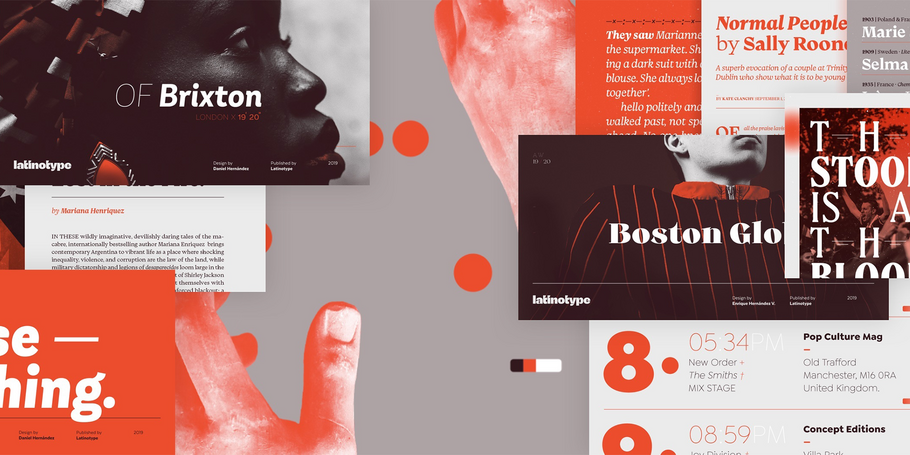
Sélectionnés par le Monotype Studio.
Latinotype.
Première fonderie numérique du Chili, Latinotype a pour objectif de "concevoir de nouvelles polices de caractères en remixant les diverses influences liées à notre identité sud-américaine avec des produits de haute qualité pour l'industrie du design contemporain". Et c'est ce que les deux fondateurs font depuis la création de leur fonderie en 2007. Luciano Vergara et Daniel Hernández ont créé une collection de polices de caractères en pleine expansion dans un large éventail de genres. Spécialisé dans l'affichage coloré et les polices de caractères, le nom du groupe "Latinotype" souligne le lien fort qu'ils ressentent avec leur identité culturelle.
Mixta
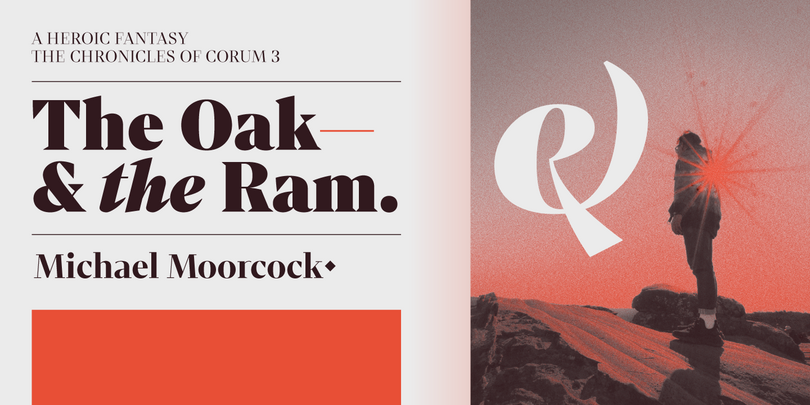
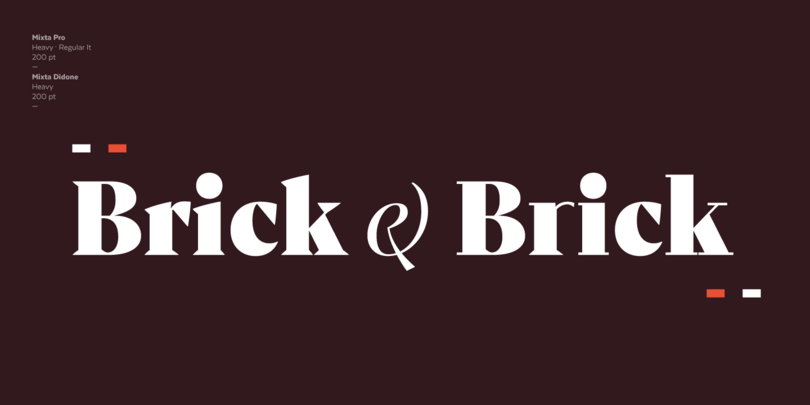
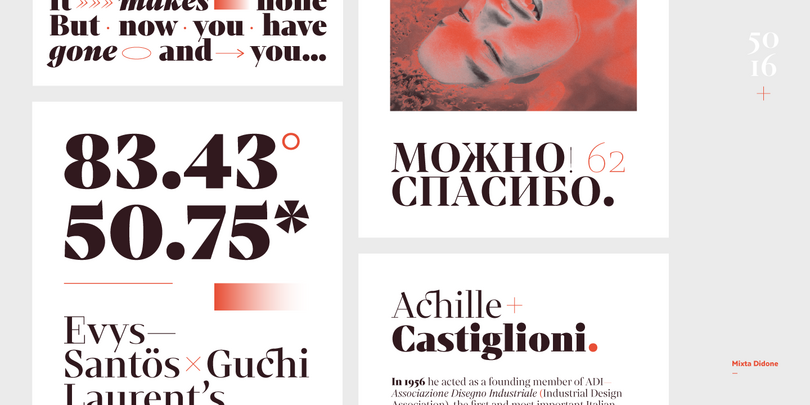
Mixta est une police de caractères sans empattement contemporain, inspirée par l’idée de mélanger différents types de terminaux afin de donner à la police une apparence singulière – des didones historiques aux sans contemporains. Mixta est proposée avec un jeu de 1200 caractères qui prend en charge plus de 200 langues latiesn. Cette police a été spécialement conçue pour la stratégie de marque, la publicité, la conception éditoriale et l’utilisation à la télévision et dans les réseaux sociaux.
Recoleta
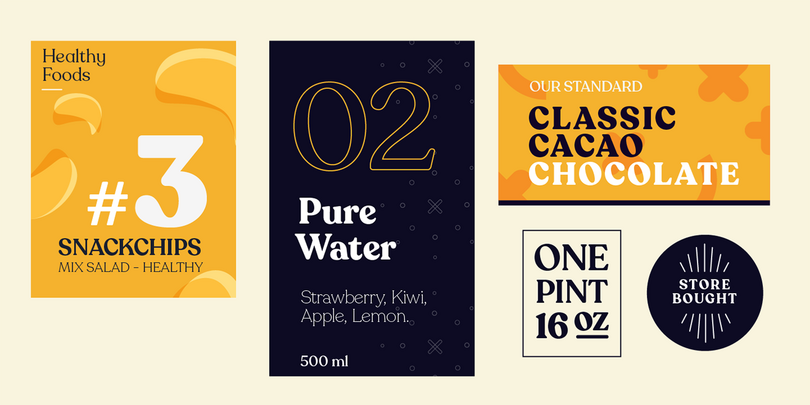
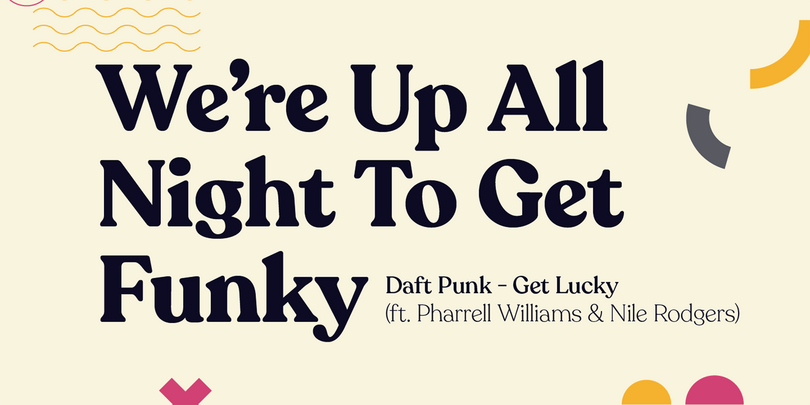
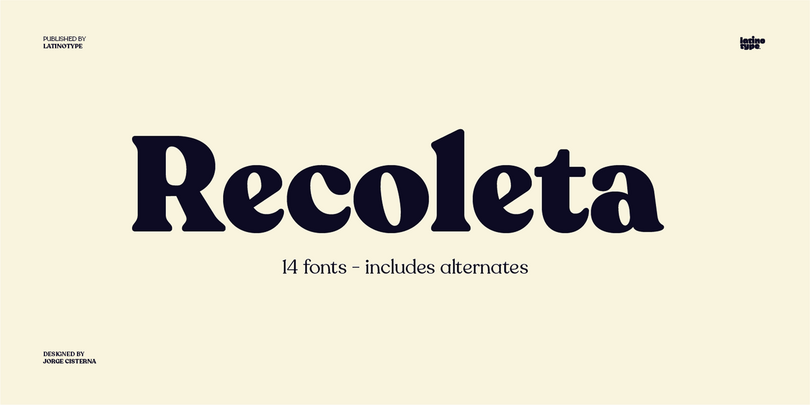
Tout comme la cuisine de grand-mère, Recoleta combine une variété d’ingrédients – de diverses polices de caractères populaires des années 1970 – comme les formes douces et délicates que l’on trouve dans Cooper ou les traits fluides et anguleux dans Windsor – mélangés en un seul design qui présente des saveurs familières, mais fraîches et modernes.
Corporative Slab
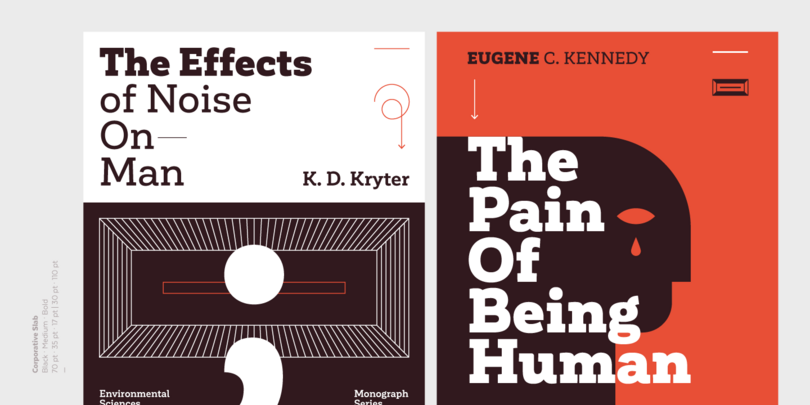
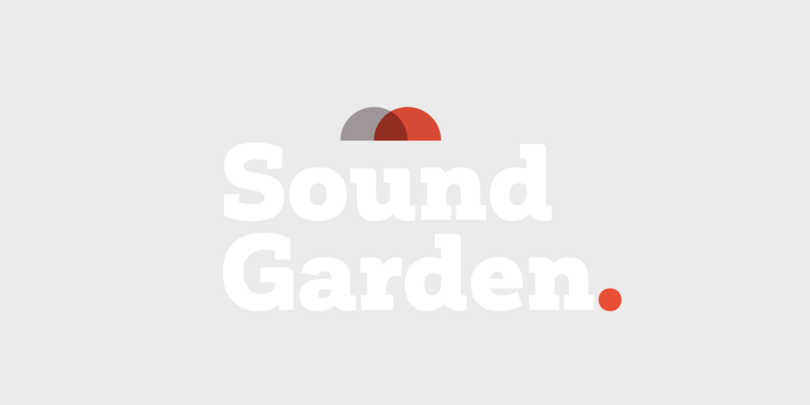
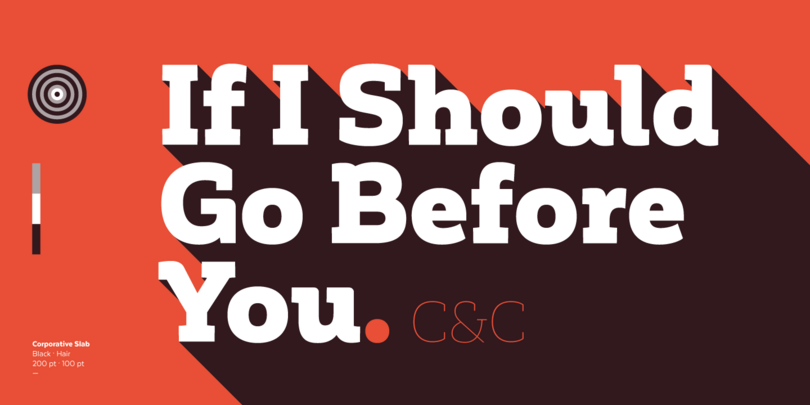
Les serifs épais du Corporative Slab lui donnent une forte personnalité. Son architecture fondamentale et ses bords arrondis lui confèrent un équilibre parfait avec le Corporative original. Le Corporative Slab est idéal pour une utilisation à grande échelle et convient également aux petites tailles.
Branding
Branding, une police de caractères moderne pour des besoins modernes ! Elle a été spécialement conçue pour répondre aux besoins esthétiques et fonctionnels contemporains ; l’interprétation d’un caractère moderne du point de vue du concepteur. Cette police convient bien aux logos, aux isotypes, aux textes courts, etc. Elle se décline en 7 graisses, allant du Thin au Black, avec les italiques correspondantes, et comprend un jeu de 544 caractères qui supporte 128 langues différentes. Les accents européens, les chiffres à l’ancienne et les multiples variantes sont également inclus.
Galeana
Galeana est une réinterprétation des polices de caractères à saveur latino-américaine utilisées pour les conceptions éditoriales européennes telles que les magazines Plastique et Zembla. Cette superfamille est composée de 4 sous-familles : Compressed, Condensed, Standard et Extended. Les variantes les plus lourdes et les plus étroites – créées au début du processus de conception – ressemblent aux troncs élancés des Galenas (tulipiers africains). Les autres variantes ont une largeur étendue, ce qui évoque la forme large de la couronne de ces arbres.
Trenda
Trenda est une police de caractères géométrique sans empattement basée sur la majuscule du Trend, une police de caractères latinotype populaire, commercialisée en 2013. Les variantes les plus légères et les plus lourdes de Trenda sont idéales pour l’affichage, tandis que ses graisses moyennes conviennent bien aux textes courts et moyens. Cette police a été spécialement conçue pour les projets d’entreprise, les logotypes et l’édition.
Arquitecta
Arquitecta – une typographie humaniste comme projet rationnel. Inspirée par la typographie manuelle américaine et européenne de la première moitié du siècle dernier, Arquitecta trouve son propre espace comme une excellente alternative pour les paragraphes devant des classiques comme Futura, Kabel ou Avant Garde. Basée sur l’expérimentation du Bauhaus et de la modernité sans histoire, Arquitecta a été inspiré pour construire une police de caractères géométrique rationnelle aux proportions humanistes, adaptée à la mise en page et à la lecture continue du texte.
Andes Neue
Sympathique, neutre et joyeuse, cette police de caractères est parfaite pour les projets de marque. Andes Neue est une version redessinée de Andes, avec un jeu de caractères plus grand de 759 glyphes qui prend en charge 219 langues latines de 212 pays, petites majuscules inclues !
Mohr
Mohr convient à un large éventail d’applications, de l’écran au petit texte. La famille Mohr se décline en trois versions : normale, alt et italique, chacune avec 9 graisses de police, de Thin à Heavy, ce qui donne un total de 27 polices. Mohr comprend également des éléments initiaux et terminaux dans la plupart des caractères majuscules et minuscules. Cela donne à la police une personnalité unique et permet une plus grande variété d’utilisations, comme la création d’une marque et d’un emballage.
Moranga
Texta
Texta. Une police sans empattement pour tous. En étudiant les modèles des humanistes d’Edward Johnston à Adrian Frutiger et l’alphabet gothique des peintres de signes, on obtient Texta, un sans empattement contemporain, rationnel, transparent et utile pour composer toutes sortes de textes. Latinotype a développé une version Alt qui remplace les minuscules comme a-g-y par des constructions géométriques pour plus de polyvalence.